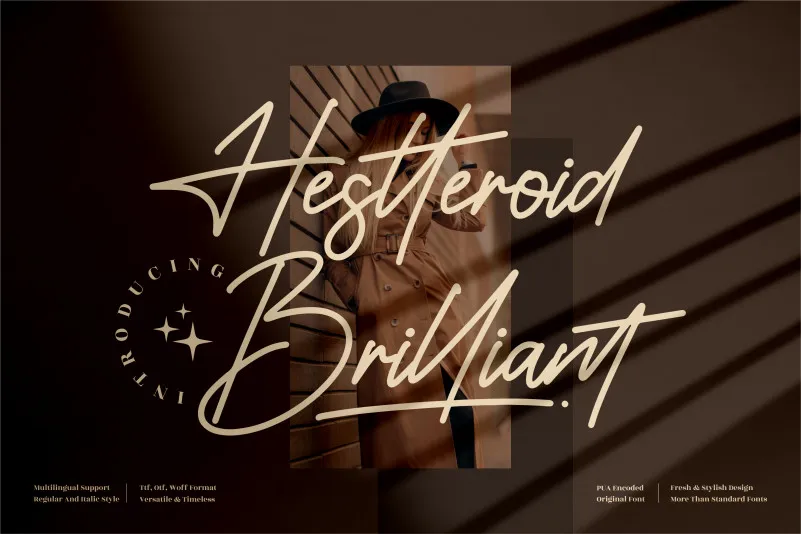
Hestteroid Brilliant Font – Download Grátis
A fonte Hestteroid Brilliant é uma criação do designer perspectype, adequada para diversas aplicações criativas. Seja para trabalhos de identidade visual, como logomarcas e projetos de marca, ou até mesmo para design de prateleira, embalagens de produtos, talheres, cartões de agradecimento, capas de livros, embalagens de sapatos, etiquetas em lojas online e muito mais. Esta fonte é perfeita para projetos que exigem um toque de sofisticação e elegância. Seja uma camiseta personalizada, um cartão de visita ou até mesmo uma capa de livro, Hestteroid Brilliant será seu parceiro ideal em qualquer projeto criativo. Com seu design único e estilo tipográfico chamativo, você pode fazer a diferença em seus projetos. Sua versatilidade faz com que seja perfeita para tudo o que pretende expressar através da fonte.